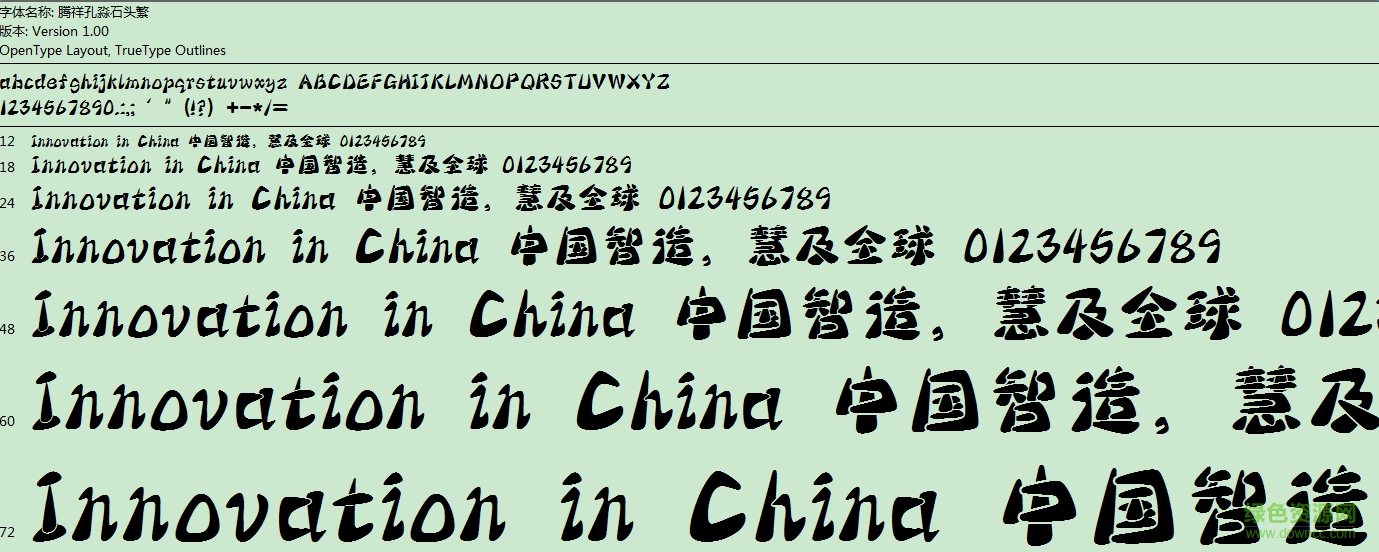
騰祥孔淼石頭繁體是一款騰祥出品的繁體字體,字形美觀有趣,美工設(shè)計(jì)、海報(bào)設(shè)計(jì)等方面都可以使用,小編為大家?guī)砻赓M(fèi)下載地址,歡迎大家來綠色資源網(wǎng)踴躍下載哦!
騰祥孔淼石頭繁體,一款非常有趣的字體,適用于廣告方面,字形工整,又充滿力量。